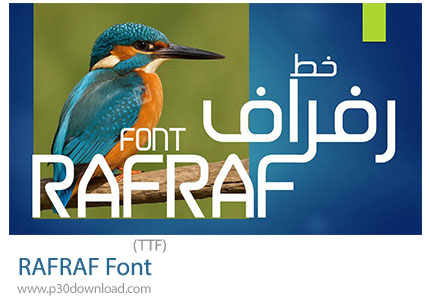
دانلود RAFRAF Font دانلود فونت عربی و انگلیسی رفراف
در این بخش شاهد فونت عربی و انگلیسی رفراف می باشید که با فرمت TTF بر روی سایت برای دانلود قرار گرفته است. فونتH RAFRAF یک فونت عربی مدرن و زیباست که با هدف ایجاد خوانایی بالا و طراحی چشمنواز ساخته شده است. این فونت صرفاً بر پایه حروف عربی طراحی شده و ممکن است نسخهای ویژه بدون پشتیبانی از حروف لاتین (انگلیسی) باشد. رفراف یک فونت عربی با طراحی معاصر است که به خوبی میتواند در طراحیهای حرفهای مورد استفاده قرار گیرد.